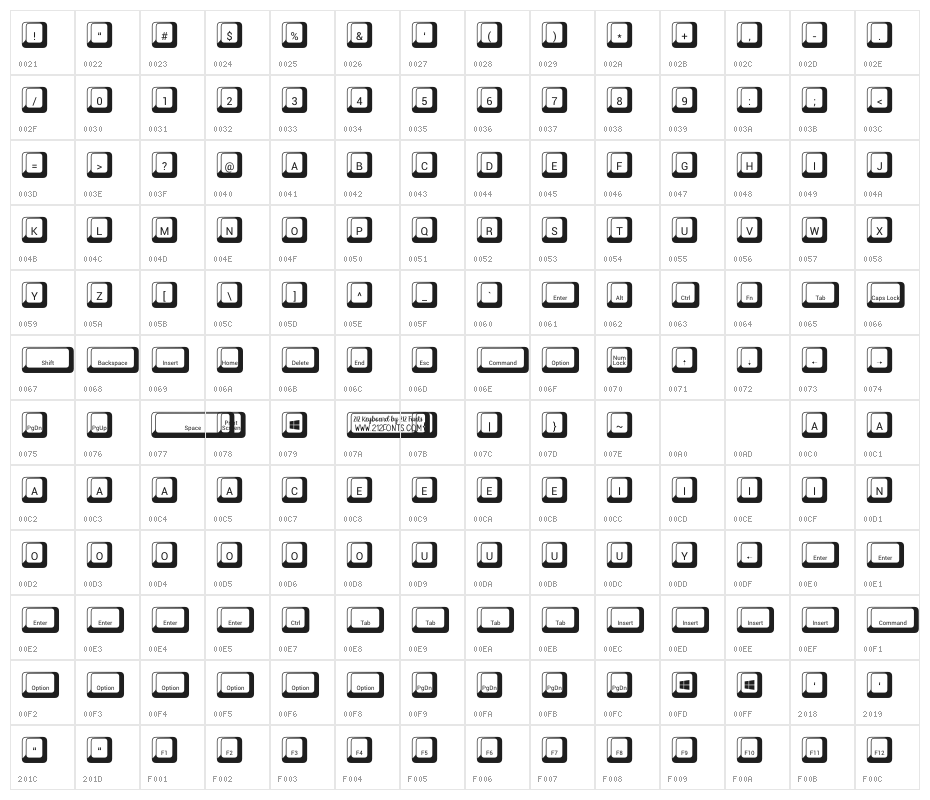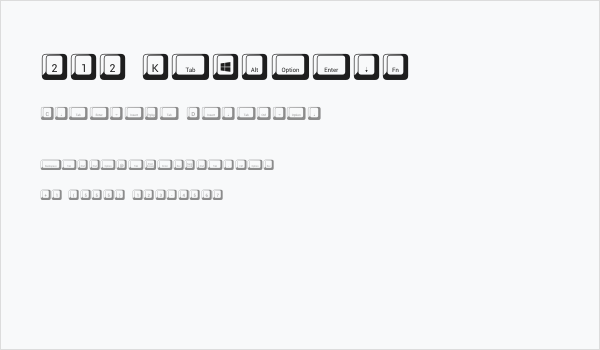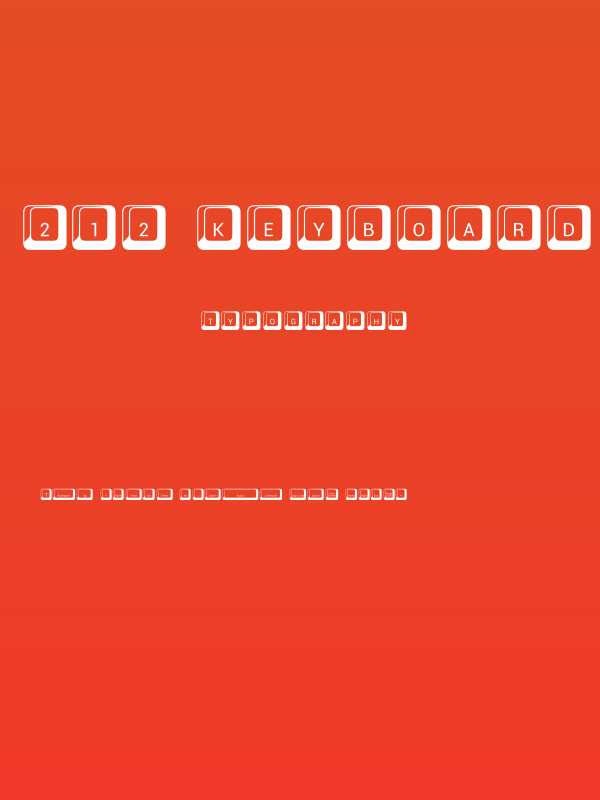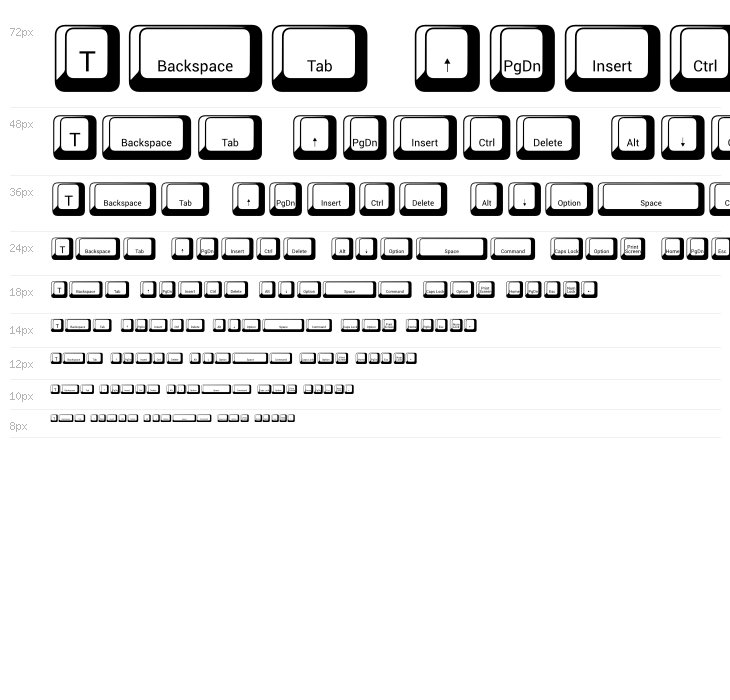
212 Keyboard Font
| Caso d'uso | Logos, Headlines, Digital Art |
| Progetti proposti | Ideal for tech-related designs, digital art projects, educational materials, or any creative work that benefits from a modern, tech-inspired aesthetic. |